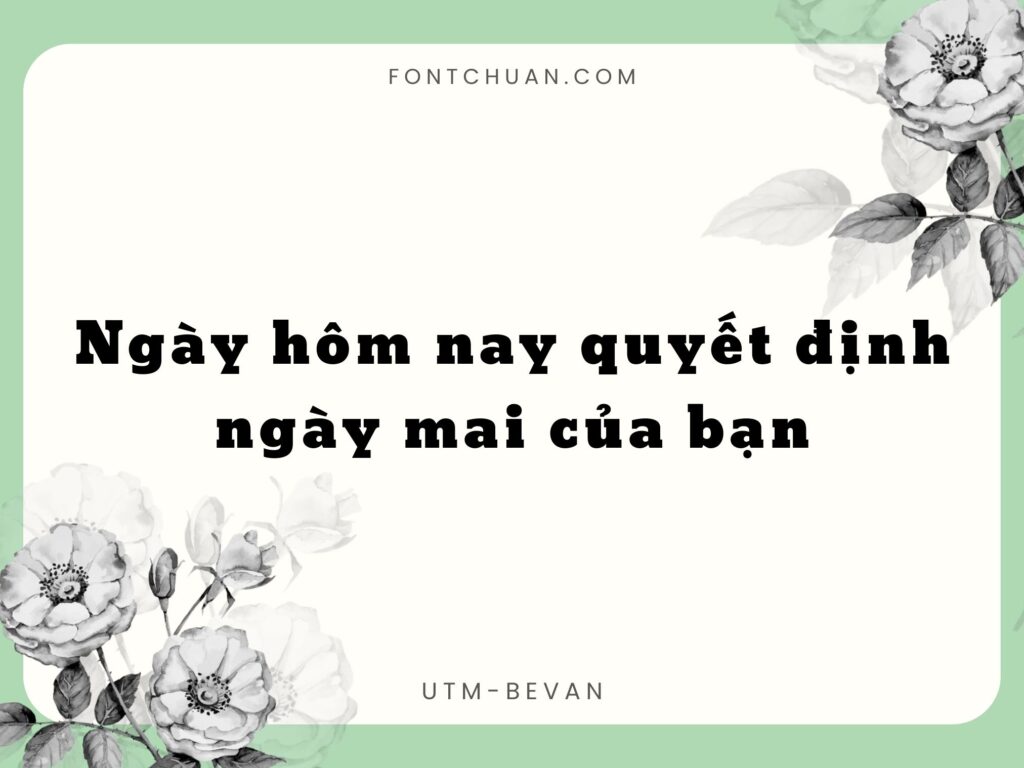
Font UTM Bevan Việt Hóa
UTM Bevan là phiên bản Việt hóa của font chữ Bevan, một Font Slab Serif được thiết kế lại bởi Vernon Adams, dựa trên nguyên mẫu từ thập niên 1930 của Heinrich Jost.
Font này nổi bật với các ký tự in hoa, đường nét dày dặn và mạnh mẽ, tạo cảm giác cổ điển pha lẫn hiện đại, mang phong cách Font Vintage đặc trưng của những thiết kế thập niên trước. Phiên bản Việt hóa đã được thực hiện, hỗ trợ đầy đủ tiếng Việt cùng hơn 100 ngôn ngữ khác. Đây là một trong những font được cộng đồng thiết kế sưu tầm và chọn lọc nhằm đáp ứng nhu cầu đa dạng trong thiết kế.
UTM Bevan có cấu trúc chữ với các nét thẳng và độ dày đồng đều, tạo nên sự rõ ràng và dễ đọc. Font này phù hợp cho các ứng dụng như thiết kế tiêu đề, logo, áp phích và các ấn phẩm in ấn yêu cầu sự nổi bật và mạnh mẽ. Đồng thời, nhờ sự thanh thoát trong các ký tự, UTM Bevan cũng có thể được ứng dụng như một Font chữ spa, mang đến cảm giác sang trọng, nhẹ nhàng và tinh tế cho các thương hiệu chăm sóc sức khỏe, spa và làm đẹp. Các ngành nghề như quảng cáo, giáo dục, công nghệ và bất động sản đều có thể tận dụng UTM Bevan để tạo điểm nhấn độc đáo trong thiết kế.